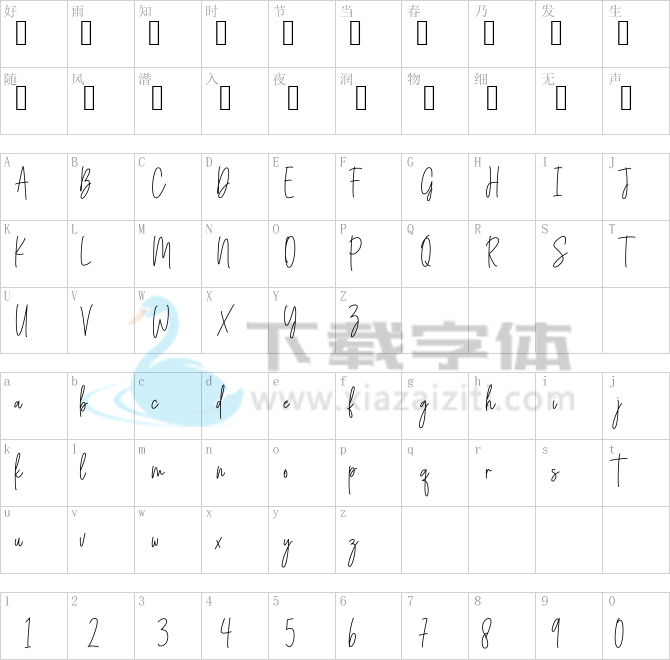
Angelica Jealous.ttf字体下载,这款字体结构工整、笔画清晰,兼顾美观与易读性,适用于标题、正文、海报、包装、LOGO 等多种场景。字形优雅稳定,风格百搭耐看,适配日常排版与创意设计,让文字呈现更舒适、更具质感。Angelica Jealous.ttf字体下载一笔一画,皆是细节,以均衡的比例、流畅的线条打造舒适视觉体验,字形端正大气,风格简约现代。无论是商业设计、品牌宣传还是日常排版,都能轻松驾驭,让文字更有格调与力量。Angelica Jealous.ttf字体下载字体下载。